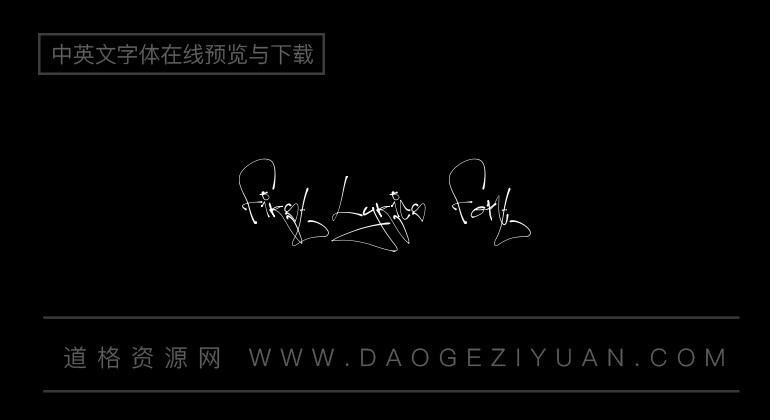
First Lyrics字体是一种手写风格的字体,采用了轻盈的线条和流畅的曲线,适用于制作歌词、手写笔记、海报设计等场合。这种字体风格独特,具有很好的可读性和美学感受,使得文本内容看起来更加生动和有趣。 First Lyrics字体包括两种不同的风格:First Lyrics Bold和First Lyrics Regular。First Lyrics Bold字体加粗了线条,更加突出,适用于需要突出强调的场合;而First Lyrics Regular字体则更加柔和,适用于需要温和效果的场合。 First Lyrics字体适用于多种设计场合,尤其适合于音乐、艺术、文学等领域的设计。此外,该字体可以在多种设计软件上使用,并且可以在多种平台上使用,包括Windows、Mac、iOS和Android等。内容介绍
First Lyrics Font是一款非常不错的手写艺术字体,具有很好的视觉感,适合于文化类的宣传设计、商业类品牌的广告和产品包装设计以及个性化文字排版等较多场景。